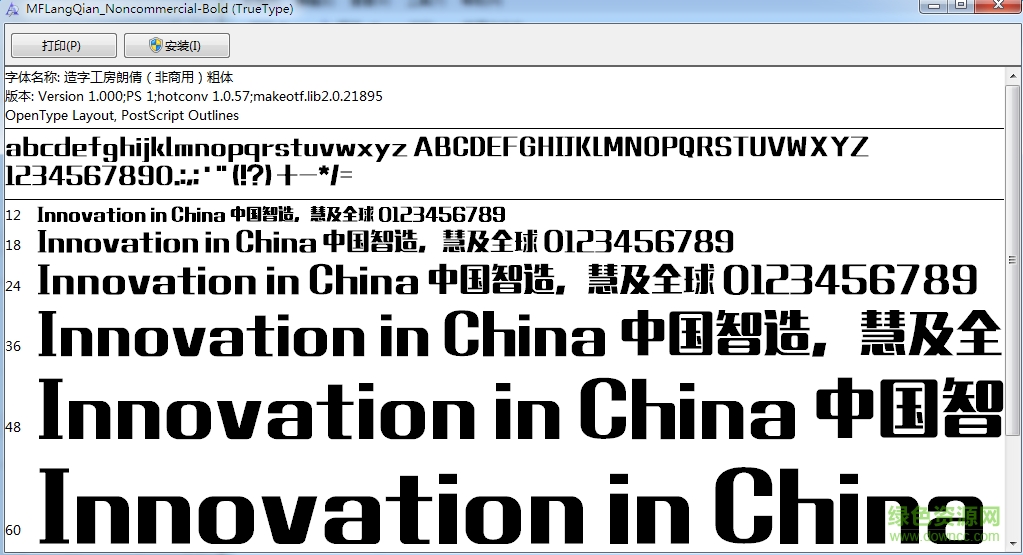
造字工房朗倩粗體是造字工房推出的一款筆法簡單,但是高端大氣的電腦字體,字體雄厚磅礴,看上去非常具有震撼力,適用于各種設(shè)計,喜歡的朋友歡迎來綠色資源網(wǎng)下載!
造字工房朗倩粗體,筆畫簡潔、粗細分明,中正不失圓潤,曲線流暢,結(jié)構(gòu)穩(wěn)重大方,整套字形柔和飽滿,如玉似珠,為漢字灌注了無限生機。整體字形姿態(tài)橫生,結(jié)構(gòu)疏朗飄逸,字里行間蘊藏一種閑適沉靜之美。